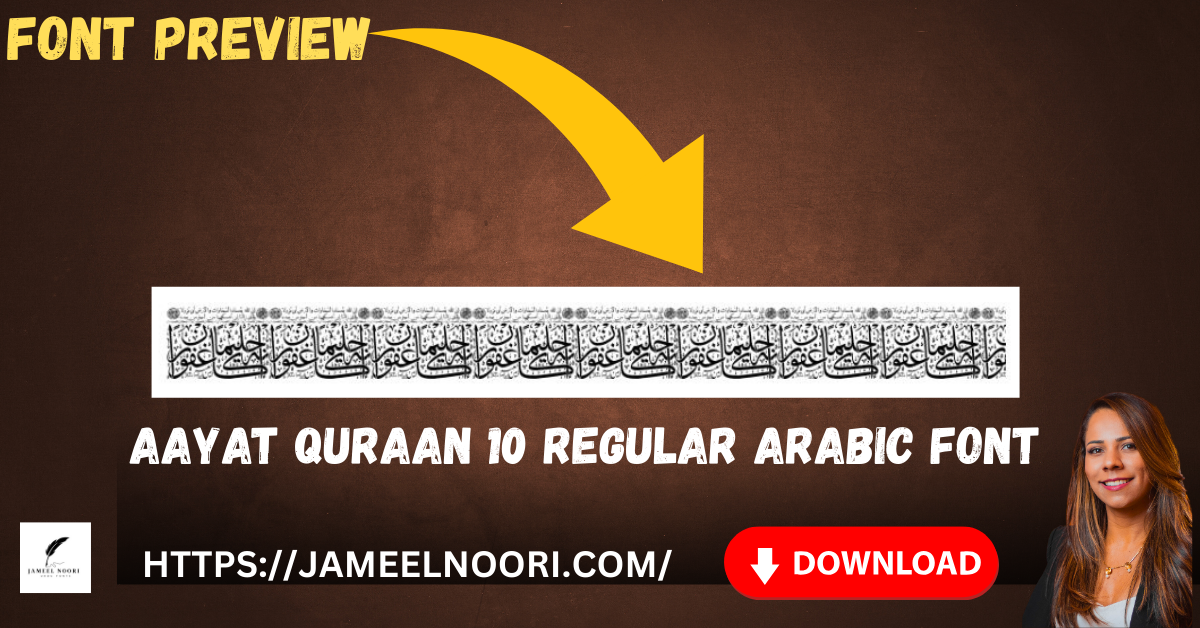
Aayat Quraan 10 Regular Arabic Font ek professional TrueType font hai jo Arabic calligraphy aur Urdu fonts lovers ke liye specially design kiya gaya hai. Ye font ab tak 8952 downloads ke saath popular ho chuka hai aur 100 users ne 4.33/5 rating di hai. Is font ki calligraphy samajhne ke liye aap Character Map section check kar sakte hain.
Why Choose Aayat Quraan 10 Regular Arabic Font
Aayat Quraan 10 Regular Arabic Font ka use karne ke bohot se benefits hain. Ye font digital projects, graphic designing, aur Quranic calligraphy ke liye perfect hai. Agar aap Urdu fonts aur Arabic fonts ke shaukeen hain, to ye font aapke liye best choice hai.
- Easy to read aur professional look.
- Perfect for Arabic font download aur best Arabic font requirements.
Features of Aayat Quraan 10 Regular Arabic Font
Aayat Quraan 10 Regular font ke khas features ye hain:
| Feature | Description |
| Style | Regular |
| Use Case | Graphic design, Quranic text, Urdu & Arabic Fonts |
Applications of Aayat Quraan 10 Regular Arabic TTF
Aayat Quraan 10 Regular Arabic Font ke bohot saare applications hain:
- Graphic Designing: Social media posts aur banners me use hota hai.
- Print Media: Books, magazines aur brochures me professional look deta hai.
- Digital Projects: Websites aur blogs ke liye best option.
- Quranic Text: Quran aur Islamic content design me widely use hota hai.
Tips for Using Aayat Quraan 10 Regular Arabic Font
Agar aap best Arabic font experience chahte hain to kuch tips follow karein:
- Bold aur italic combinations try karein for attractive headings.
- Urdu fonts ke sath combine karke modern design create karein.
- Always check Character Map before starting large projects.
Common Mistakes While Using Aayat Quraan 10 Regular
- Low-resolution export karna – ye font ki beauty ko affect karta hai.
- Font size bohot chota rakhna – readability kharab hoti hai.
- Urdu aur Arabic fonts ko mix incorrectly use karna – design messy lagta hai.
Aayat Quraan 10 Regular Arabic Font Pakistan me Urdu aur Arabic fonts ke shaukeen users ke liye ek ultimate choice hai. Is font ka use karke aap apne graphic design aur Quranic projects me professional aur modern look la sakte hain. Ye font easy-to-install, readable, aur aesthetically appealing hai, jo aapke digital aur print media projects ke liye perfect hai.
What is Aayat Quraan 10 Regular Arabic Font?
It is a TrueType Regular font specially designed for Arabic and Urdu calligraphy projects.